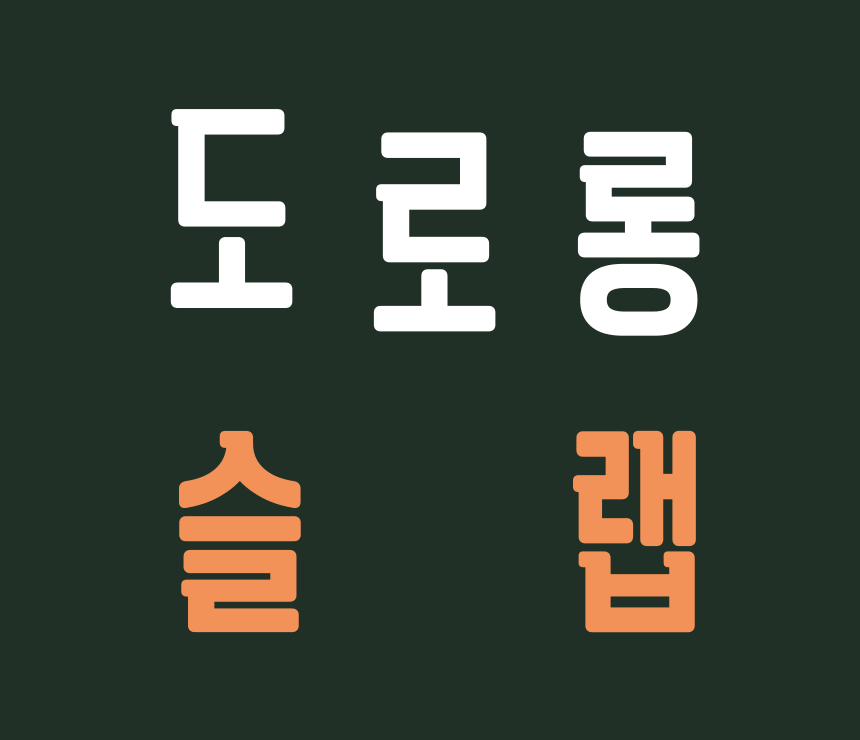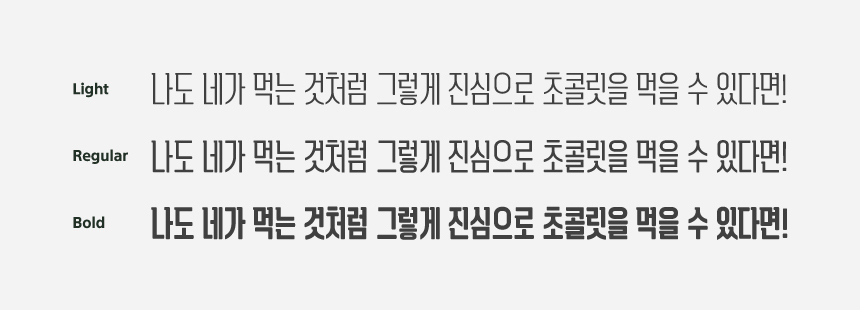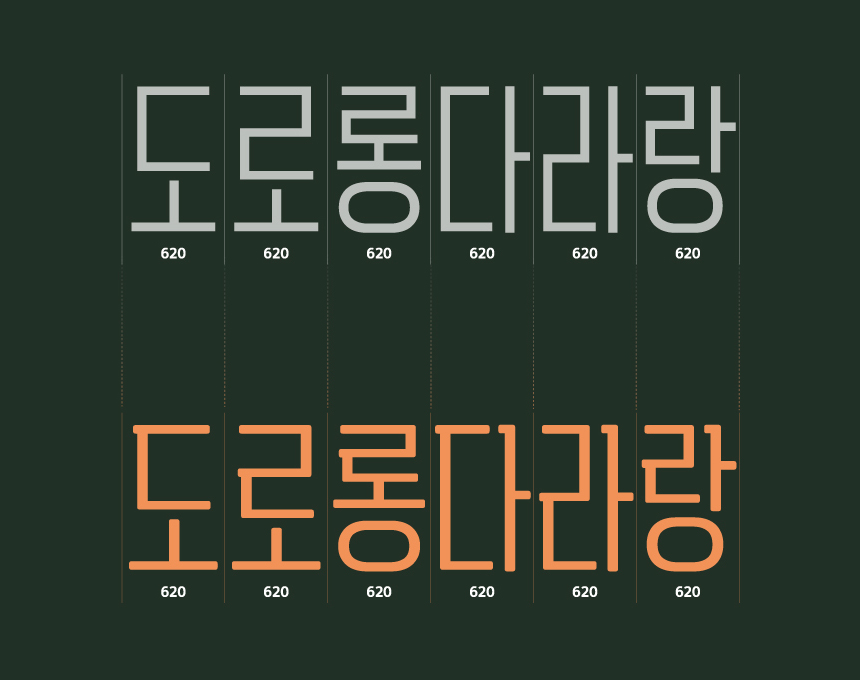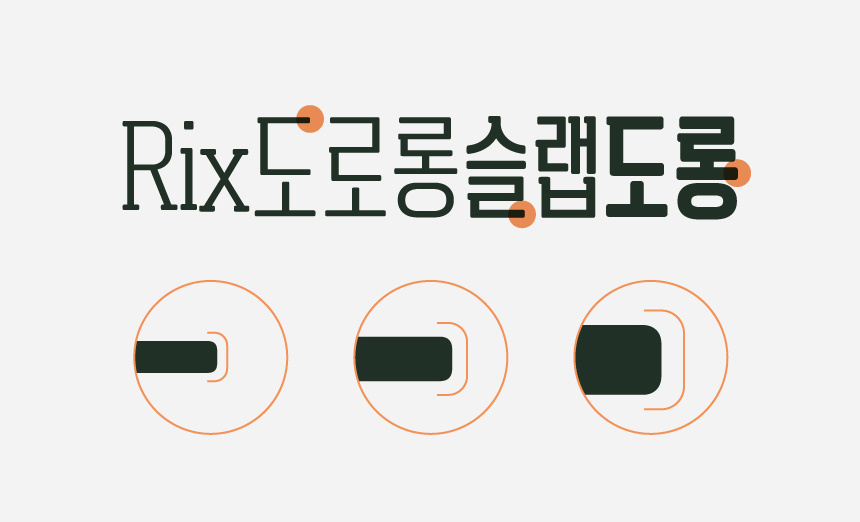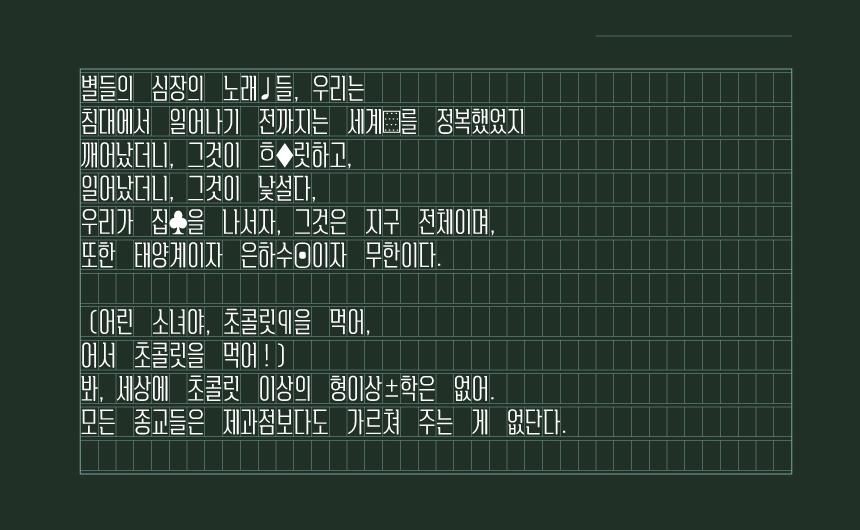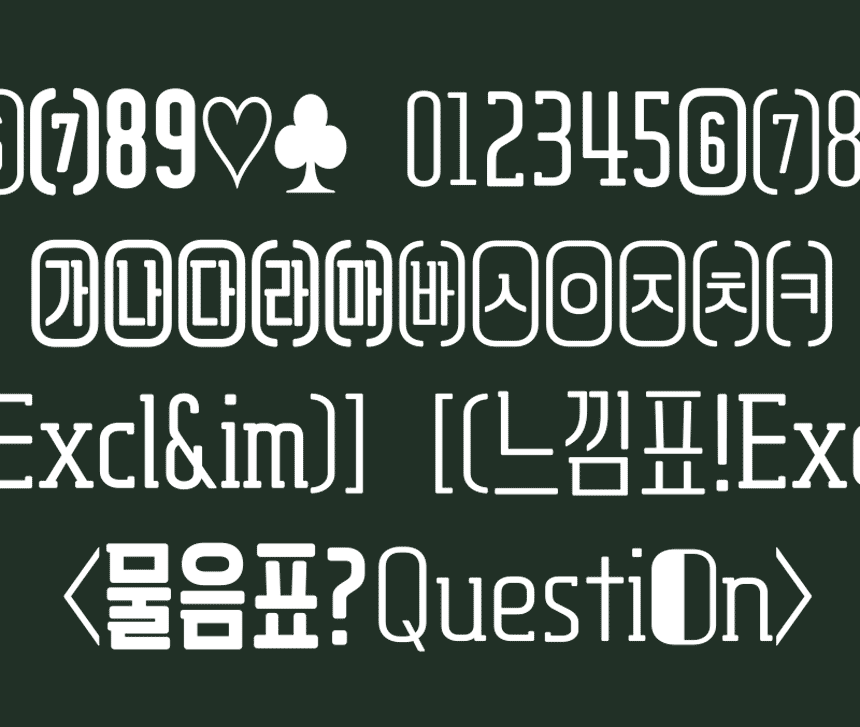
안녕하세요. 오늘은 따뜻해지는 4월의 날씨와 함께 찾아온 도로롱 시리즈의 새로운 패밀리, 「Rix도로롱슬랩」을 소개합니다! 시원시원한 장체 스타일의 제목용 서체 Rix도로롱에 부드러운 슬랩 세리프(Slab serif; 세리프가 두껍고 각진 서체)를 추가해 독특하면서도 신선함이 느껴지는데요. 도로롱 시리즈의 창시자(!)인 유현주 디자이너와의 인터뷰를 통해 더 자세한 이야기 담아봤어요.
4월의 신서체 Rix도로롱슬랩은 어떻게 탄생하게 되었나요?
Rix도로롱슬랩은 지난 10월 출시한 Rix도로롱의 시리즈 중 하나입니다. 사실 처음엔 도로롱 시리즈로 만들 계획이 아니었고, 슬랩 형태의 장식 요소가 들어간 아이디어를 제시했었습니다. 이후 아이디어를 발전시키던 과정에서 여러 시행착오를 거치며 해당 특징을 도로롱에 결합해 도로롱슬랩이 탄생하게 되었습니다.
도로롱슬랩의 가장 큰 매력 포인트는?
아무래도 Rix도로롱과 시리즈이다 보니 마찬가지로 폭이 좁은 장체에 일정한 격자 모듈이 인상적이고, 굵기에 따라 한정적인 공간에 슬랩 형태가 붙는 부분이 달라진다는 것이 가장 눈에 띌 것 같습니다. 또 기존 도로롱을 사용해 보셨다면 두 개의 폰트가 어떤 다른 느낌을 갖고 있는지 비교해 보셔도 좋을 것 같아요.
폰트를 어디에 사용하면 좋을지 추천해 주신다면!
처음 슬랩 형태의 글자 시안에서는 도로롱보다 조금 더 평이 넓고 굴림이 강해 당연히 제목용으로 사용하는 것이 어울릴 것이라고 생각했습니다만, 도로롱 시리즈로 완성하고 난 뒤 실제로 여러 단어, 문장들에 적용해서 사용해 보니 Light와 Regular는 본문에 사용해도 꽤나 어울리는 것 같아요.(물론 제가 만든 아이라 객관성이 부족하지만ㅎㅎ) 그래서 얇은 굵기들은 본문에, Bold는 길지 않은 제목이나 자막용으로 적절하다고 생각합니다. 그리고 얇은 굵기도 샘플로 리플릿의 문구를 넣어봤는데 나름 잘 어울려서, 소제목이나 자막용으로 사용되어도 좋을 것 같아요:)
길쭉길쭉 도로롱 시리즈
기존 Rix도로롱 서체와 마찬가지로 세로로 긴 장체 스타일 글꼴로 제작되었습니다. 서체 굵기는 본문, 소제목, 자막 등에 쓰기 좋은 Light 와 Regular, 눈에 띄는 헤드라인이나 중제목, 자막에도 활용하기 좋은 Bold로 구성되어 있습니다.
도로롱 시리즈의 좁은 폭은 기존의 서체와는 다른 독특한 분위기를 자아냅니다. 폭이 좁지만 위아래로 넓은 공간감과 자소 간격, 그 안에서 쭉쭉 뻗은 직선 획들이 시원함을 느끼게 합니다.
여유롭고 유연한 세리프
슬랩 세리프는 위와 같이 글자와 기호를 이루는 획의 일부 끝이 돌출된 세리프가 굵은 사각 형태의 모습을 보이는 서체 스타일입니다. 기존의 슬랩 세리프 서체들과 다르게 Rix도로롱슬랩은 각이 진 부분을 부드럽게 굴려 제작되었습니다.
Light, Regular, Bold 각 두께별로 획의 마무리에 적당한 굴림을 주어 보다 여유롭고 유연한 느낌을 줍니다. 또한 자소들의 널찍한 공간감과 전체적으로 디자인에 적절한 간격 설정으로 폭이 좁아도 시원한 인상을 갖고 있습니다.
정갈한 고정폭 글꼴
Rix도로롱슬랩도 앞서 출시된 도로롱체와 마찬가지로 모든 글자의 너비를 동일하게 설정한 고정폭으로 제작되었습니다. 이는 깔끔하고 딱 떨어지는 느낌으로 글을 정갈하고 정돈되어 보이게 해 줍니다.
영문, 숫자, 약물의 디자인은 역시 한글과 동일한 특징을 갖도록 이질감 없이 제작했습니다. 세리프가 없는 모던한 느낌의 Rix도로롱과 섞어서 활용해도 조화롭게 쓸 수 있습니다.
| 이렇게 활용해 보세요
봄에 어울리는 시 구절, 영상에 어울리는 감성적이고 유니크한 자막을 완성해 보세요. 얇은 두께를 활용하면 디자인적으로 눈에 띄면서 가독성도 좋은 텍스트로 제격입니다.
도로롱 시리즈 서체의 차분하고 부드러운 매력이 봄, 가을과 같은 계절에 유난히 잘 어울리는 것 같아요. 3가지 굵기 모두 활용도가 높아 용도에 따라 여러 콘텐츠에 사용하기 좋습니다.
오늘 이렇게 도로롱 시리즈의 두 번째 패밀리가 된 Rix도로롱슬랩 서체를 만나봤습니다. 도로롱만의 깔끔담백 스타일에 세리프를 더해 신선한 폰트가 탄생한 것 같습니다. 따뜻해지는 봄날에 자주 볼 수 있는 서체가 되길 바라며🌼 올해는 부디, 모두에게 조금씩은 더 행복한 봄이 되길!